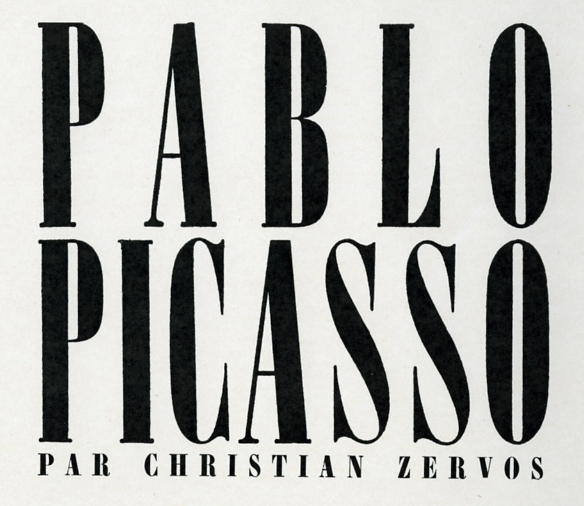
Alte, schmale (Slab-)Serif
Ob es die überhaupt digital gibt, weiß keiner …
Hier das ganze Cover, vielleicht bringen die zusätzlichen Buchstaben ja jemanden weiter …
Von den mir bekannten und hierzulande relativ weit verbreiteten schmalen klassizistischen Schriften in Blei (Arsis, Jeanette, Stephanie) isses anscheinend (anhand der 1) keine ...
Ich vermute, daß - wenn es denn wirklich eine Bleisatzschrift ist - sie wohl eher aus einer französischen Gießerei kommt ...